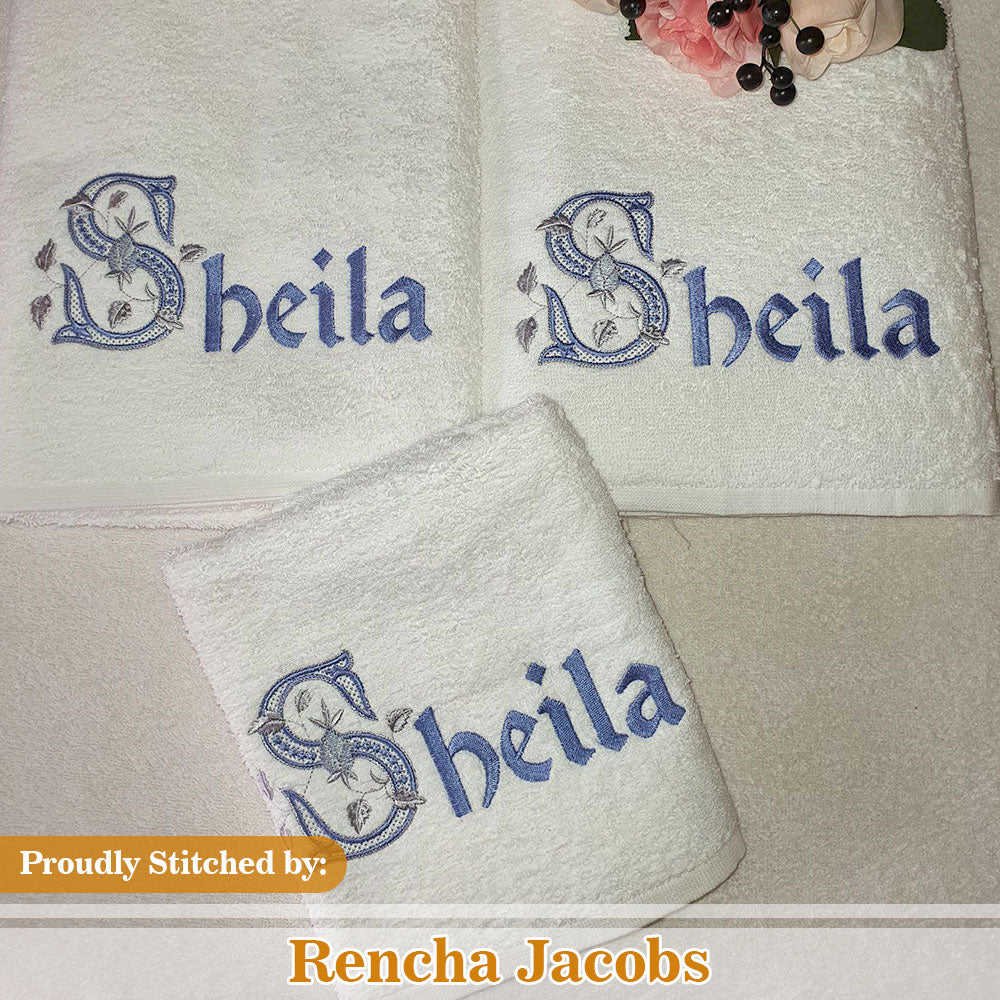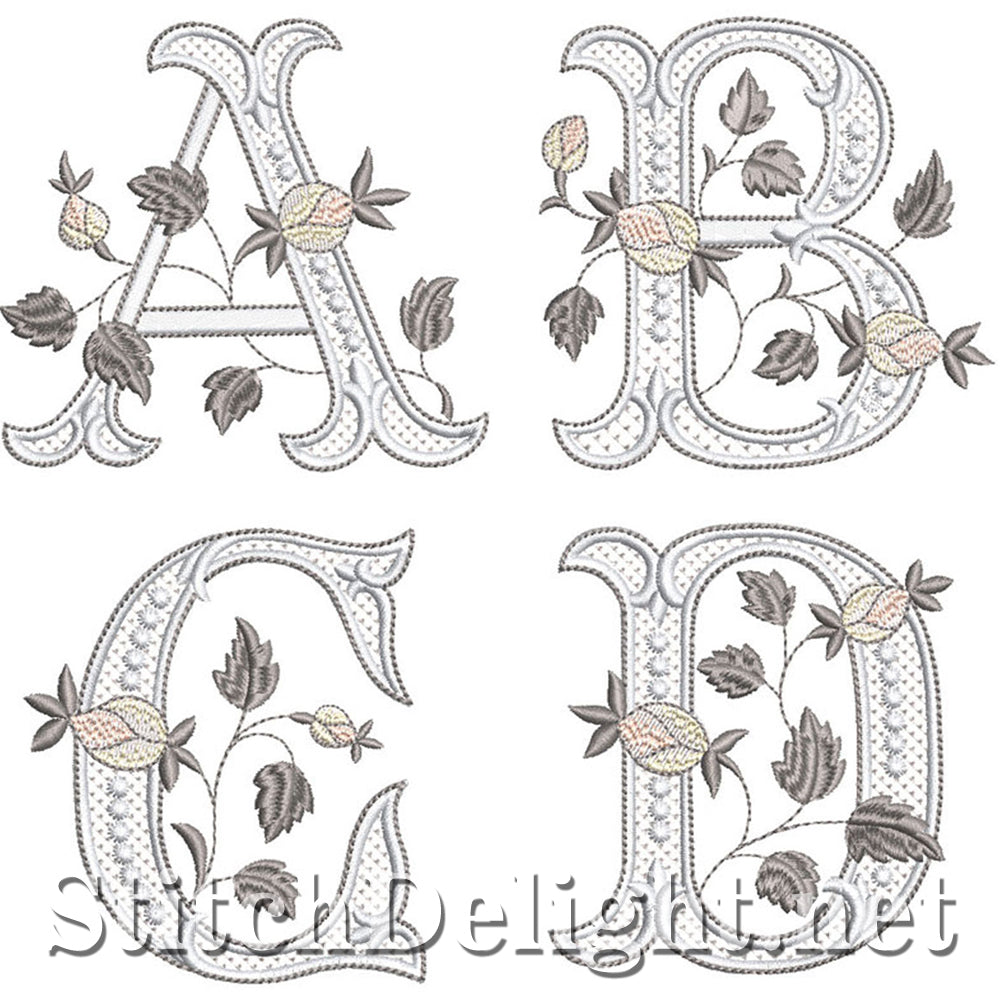
Belle police avec de superbes roses et feuilles d'argent pour le cerceau 4x4 - Hauteur des lettres 3,66" - Comprend MAINTENANT le format BX pour Embrilliance Essentials